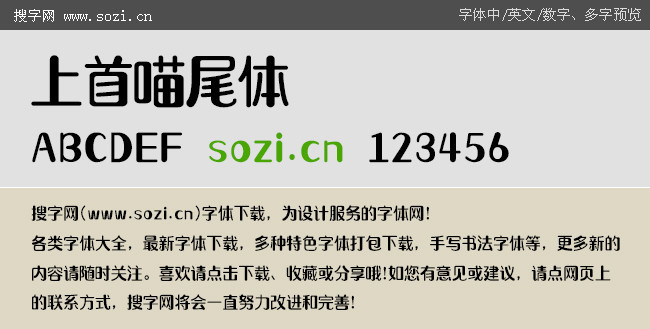
上首喵尾體
搜字網(wǎng)給大家提供一款上首喵尾體中文字體下載,上首喵尾體字體筆畫(huà)粗細(xì)對(duì)比明顯,大體粗細(xì)交錯(cuò),字體勾角處設(shè)有貓尾的特征。整體體型圓潤(rùn)可愛(ài)、賦有靈動(dòng)性。適用于搭配標(biāo)志、廣告標(biāo)語(yǔ)、商業(yè)廣告等廣告設(shè)計(jì)。